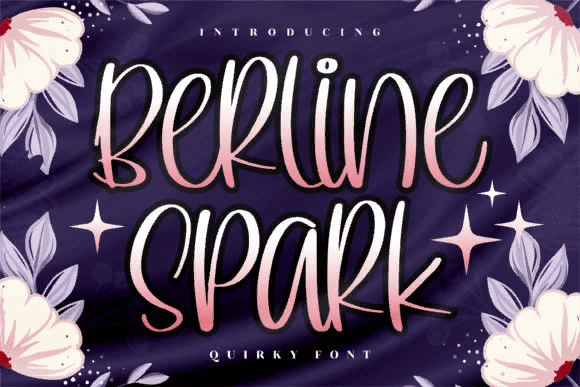
Berline Spark
- это причудливый и причудливый рукописный шрифт.
Если вы используете его для дизайна, связанного с мультфильмами, детскими играми, цитатами, заголовками, названиями брендов, обложками книг, плакатами или просто для любого творчества, требующего нотки красоты, этот шрифт - отличный выбор.